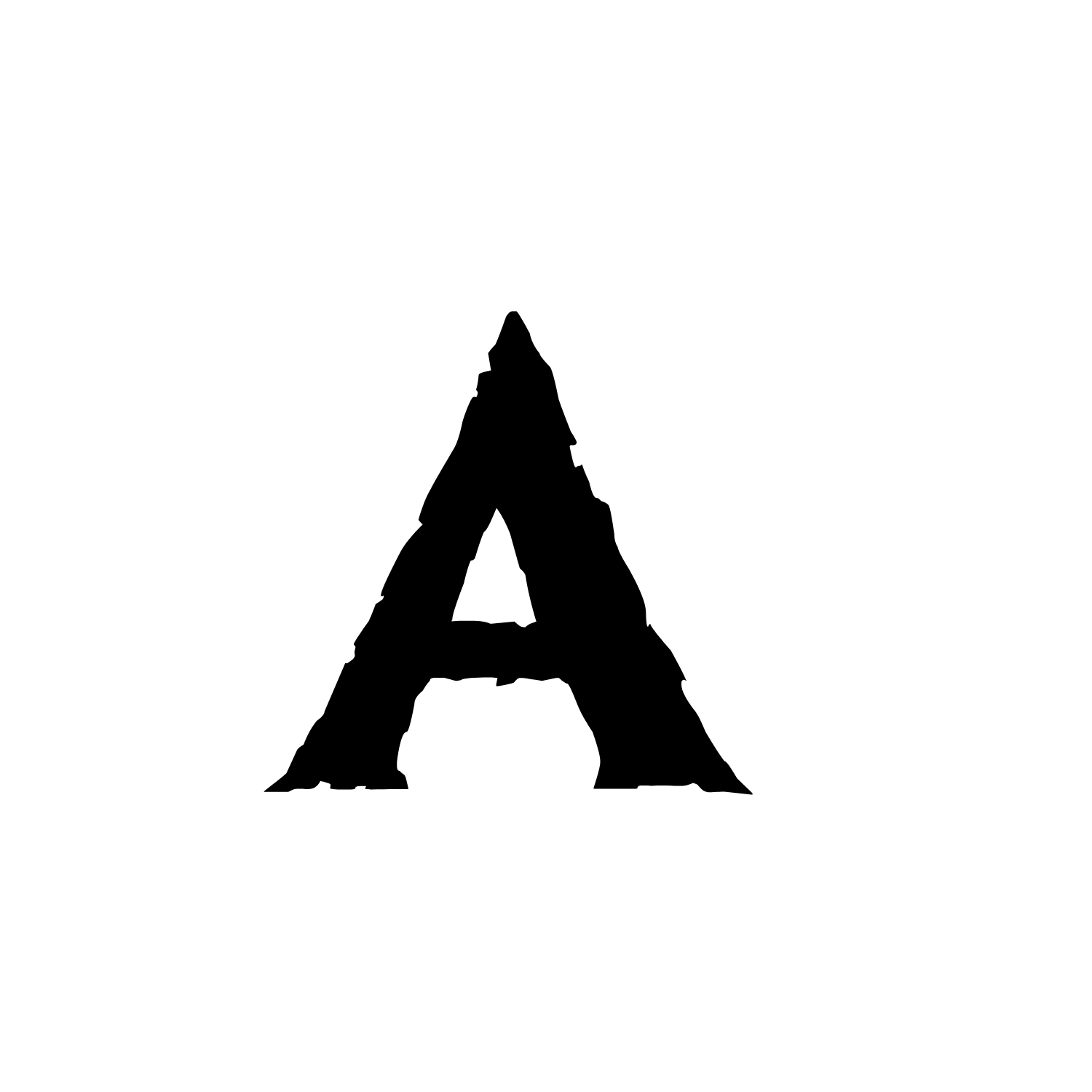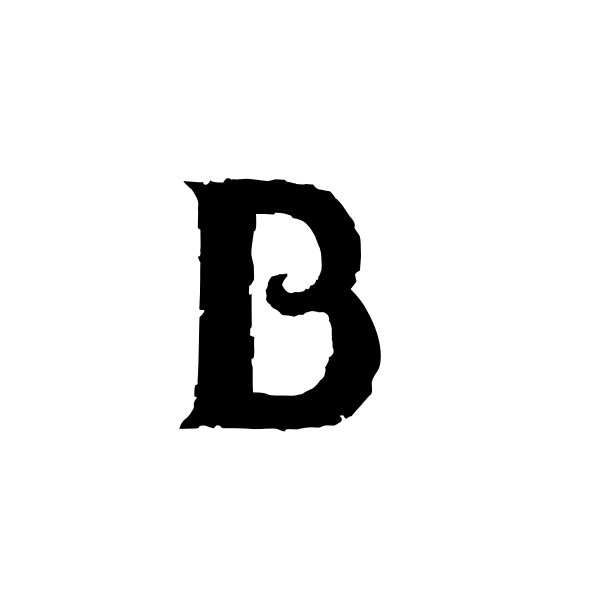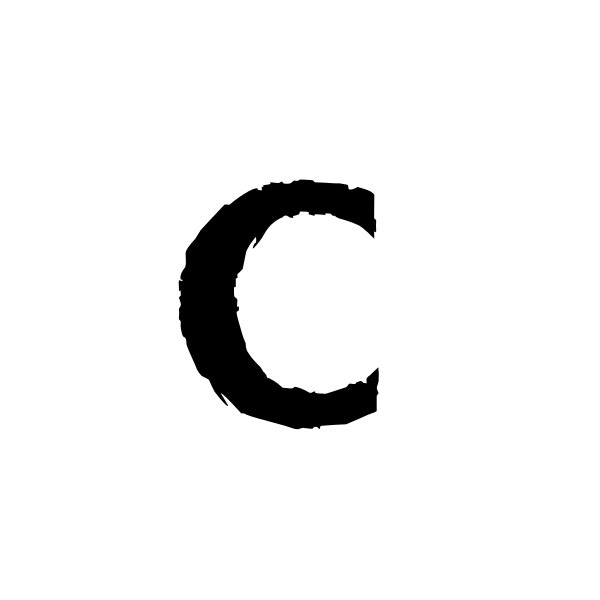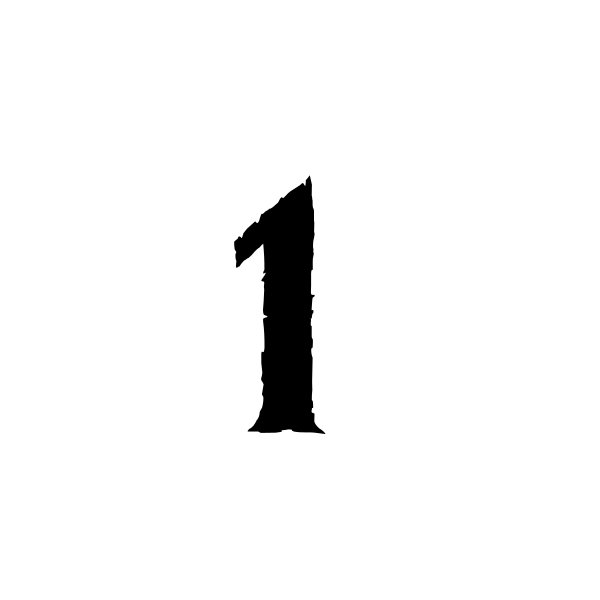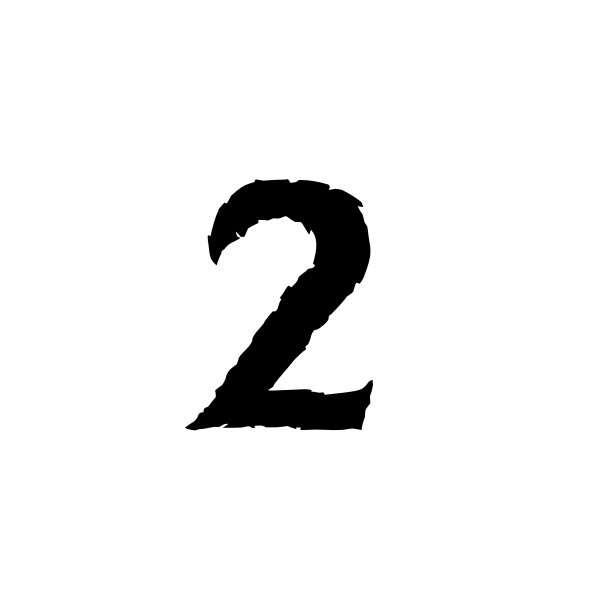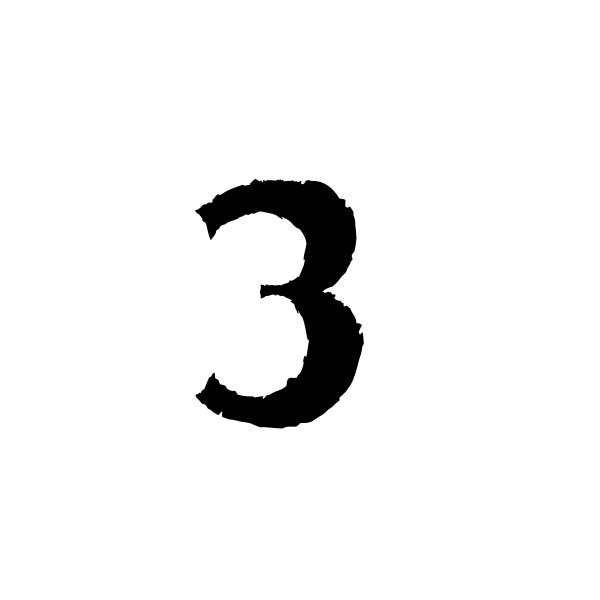
Frozen Font ist eine dekorative Schriftart im frostigen Stil – ideal für winterliche und verspielte Designs. Geeignet für Namen, Zahlen und individuelle Beschriftungen auf Textilien, Tassen, Karten oder Wanddekorationen.
Frozen Font ist eine dekorative Schriftart im frostigen Stil und eignet sich ideal für winterliche sowie verspielte Designs. Die Buchstaben wirken kühl und klar gestaltet und erinnern an eisige Formen, wodurch sie besonders gut zu saisonalen Projekten und kreativen Dekorationen passen. Der Stil bleibt dabei gut lesbar und eignet sich sowohl für kurze Wörter als auch für auffällige Überschriften.
Die Schrift ist ideal für Namen, Zahlen und individuelle Beschriftungen auf Textilien, Tassen, Karten, Geschenkverpackungen oder Wanddekorationen. Frozen Font verleiht kreativen Projekten einen winterlichen, dekorativen Charakter und sorgt für einen besonderen Blickfang in jedem Design.